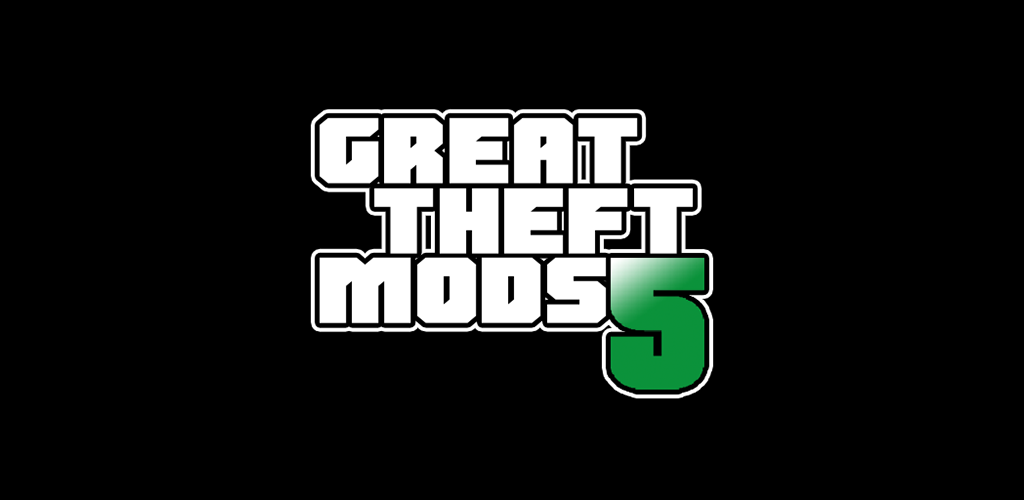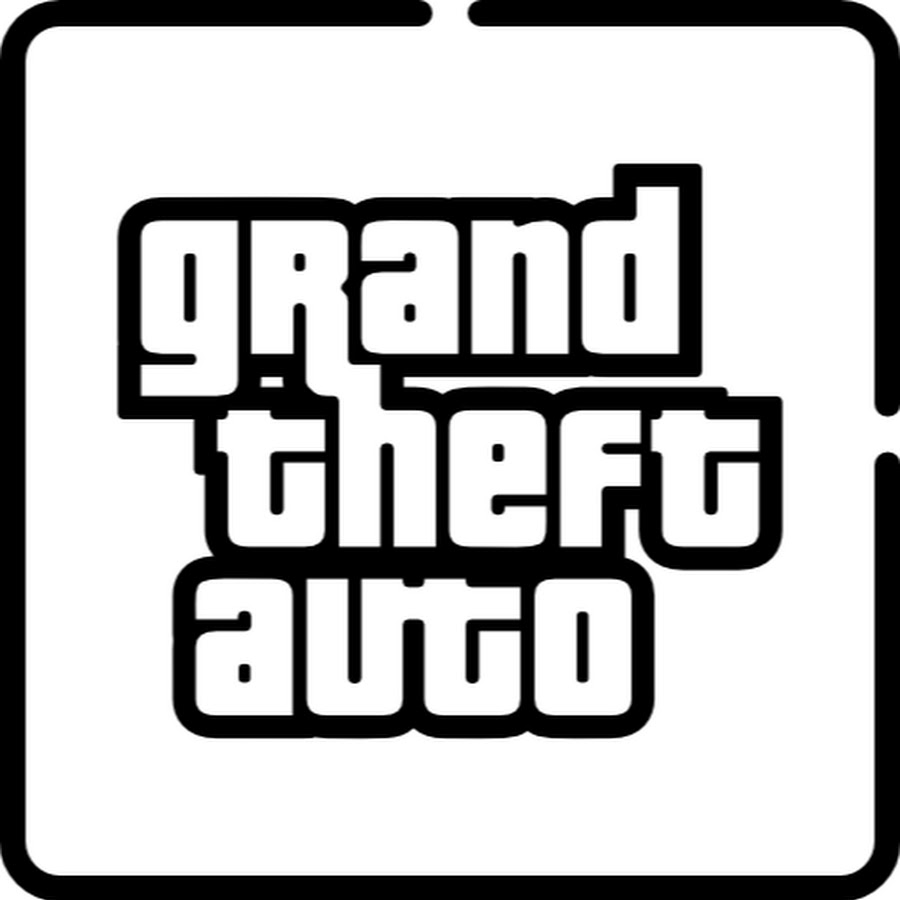
Оригинальные Шрифты GTA
Здесь вы сможете скачать шрифты популярной во всем мире игры GTA, где вам представлены как основные, или сказать главные, но и немного других, второго плана. Имеется виду, те которые идут в подписях, как основа и в самом интерфейсе. Безусловно можно здесь сказать, что он не полный, так как некоторые просто не поддерживают кириллицу, которая основном присутствует на интернет ресурсе.Сам не фанат этой игры, но реально куда не глянь в поиске, то обязательно увидишь название или изображение ее, и из этого можно сделать вывод, что она в спросе и с каждым годом все больше.
Pricedown
Этот шрифт считался самым главным в третьей части и он был на обложке. Но главная его преимущество, что он полностью поддерживает кириллицу.
Rage Italic
Old English Text
Да, этот тот самый шрифт, что была надпись San Andreas, также как многие пишут, он отлично подходит под тату, но мне кажется, дело в том, что его стиль просто шикарный.
United States
Этот тот самый шрифт из самых запоминающих, который применялся в GTA 5, кириллица с ним не идет. Но сами можете посудить, она здесь и не нужна, так как под логотип, это будет отличное решение.
Copyright House Industries
Кто то говорит, что один из самых красивых шрифтов, которые применялись в GTA 5, где еще идет полная поддержка русского языка. Здесь нужно предупредить, чтоб с ним осторожнее были, так как на его идет лицензия от Only Desktop Use. Не чего не поделаешь, так как многие идут так.
Вот она основная подборка, да она небольшая и состоит из 5 материалов, но как раз те, которые применялись во всех играх, что выходили.
Rockstar использует нелицензированный шрифт в логотипе GTA, GTA 5, новость
Как стало известно, компания Rockstar Games использует бесплатный нелицензированный шрифт для создания логотипа серии игр Gran Theft Auto с 2001 года, и, видимо, не собирается изменять своим традициям.
Услышав это, один из дизайнеров решил сформировать логотип GTA 5 на основе лично разработанного им шрифта.
Оказывается, тот материал, который использовали Rockstar Games во времена работы над логотипом для Grand Theft Auto 3, базируется на шрифте «Pricedown», впервые примененный для оформления телевизионного игрового шоу The Price Is Right, чья премьера состоялась в далеком 1956 году. Убедиться в этом можно на сравнительных изображениях, представленных ниже:
Несомненно, этот факт ни в коем случае не влияет на завидную репутацию Rockstar Games, но для талантливых дизайнеров и заядлых фанатов франшизы Gran Theft Auto эта темя является вкусной пищей для размышлений. Одним из таких людей можно назвать Мартина Шметзера, который со своими товарищами с самого начала следил за развитием криминального экшена. Их компания придерживалась мысли, что с каждой новой игрой в серии будет меняться и логотип, но после Grand Theft Auto 3 и Grand Theft Auto: Vice City стало ясно, что разработчики нашли подходящий для них вид торговой марки.
Дизайнер Мартин Шметзер склонен считать, что Grand Theft Auto 5 настолько двинулась вперед от своих предшественниц, в честь чего можно было бы и поменять «лицо» серии. В принципе, он не только высказывает свои предположения, но и демонстрирует пример хорошей модернизации логотипа, результаты чего находятся в границах этой статьи.